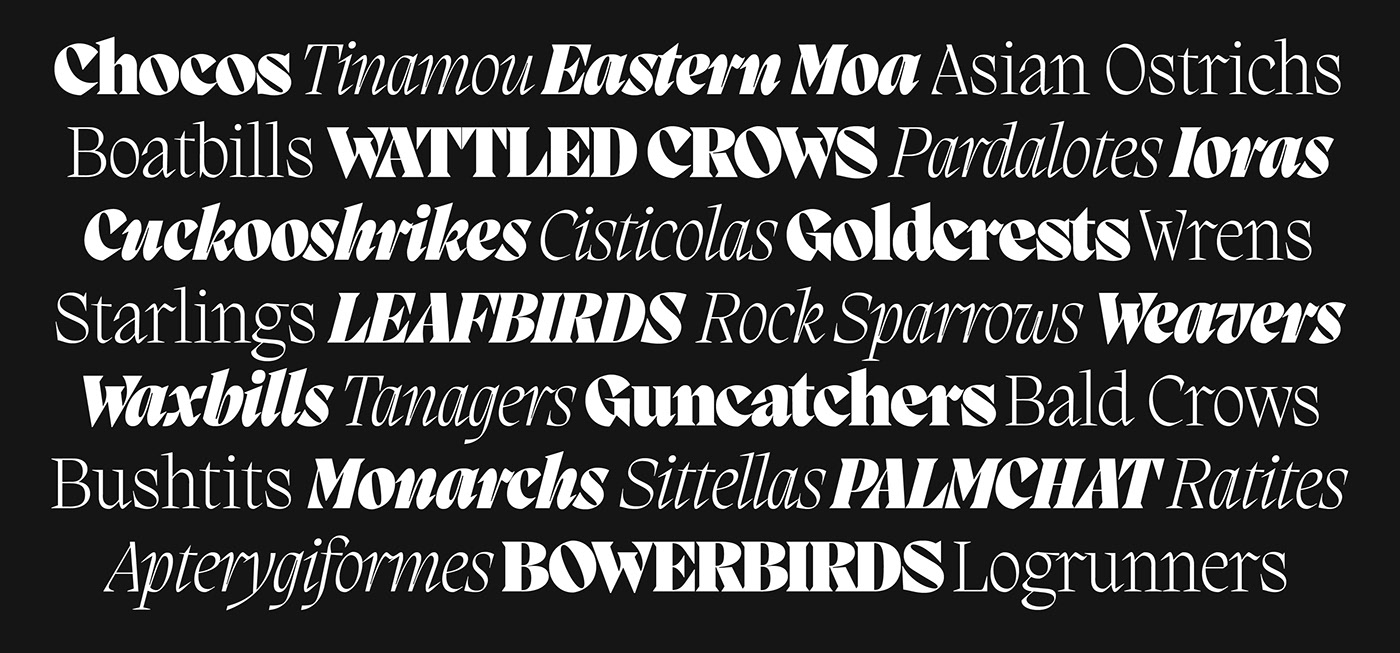
Migra là một kiểu chữ serif nhọn được lấy cảm hứng từ các đặc điểm của loài chim di cư. Trọng lượng của nó trải dài từ kiểu cắt ánh sáng khắc khổ và thanh lịch đến màu đen diều hâu và mạnh mẽ. Được đóng gói với một bộ chữ nghiêng và chữ ghép đặc biệt, kiểu chữ này được đảm bảo sẽ thêm phần lấp lánh và duyên dáng cho bất kỳ thiết kế nào của bạn.
Migra Font Family